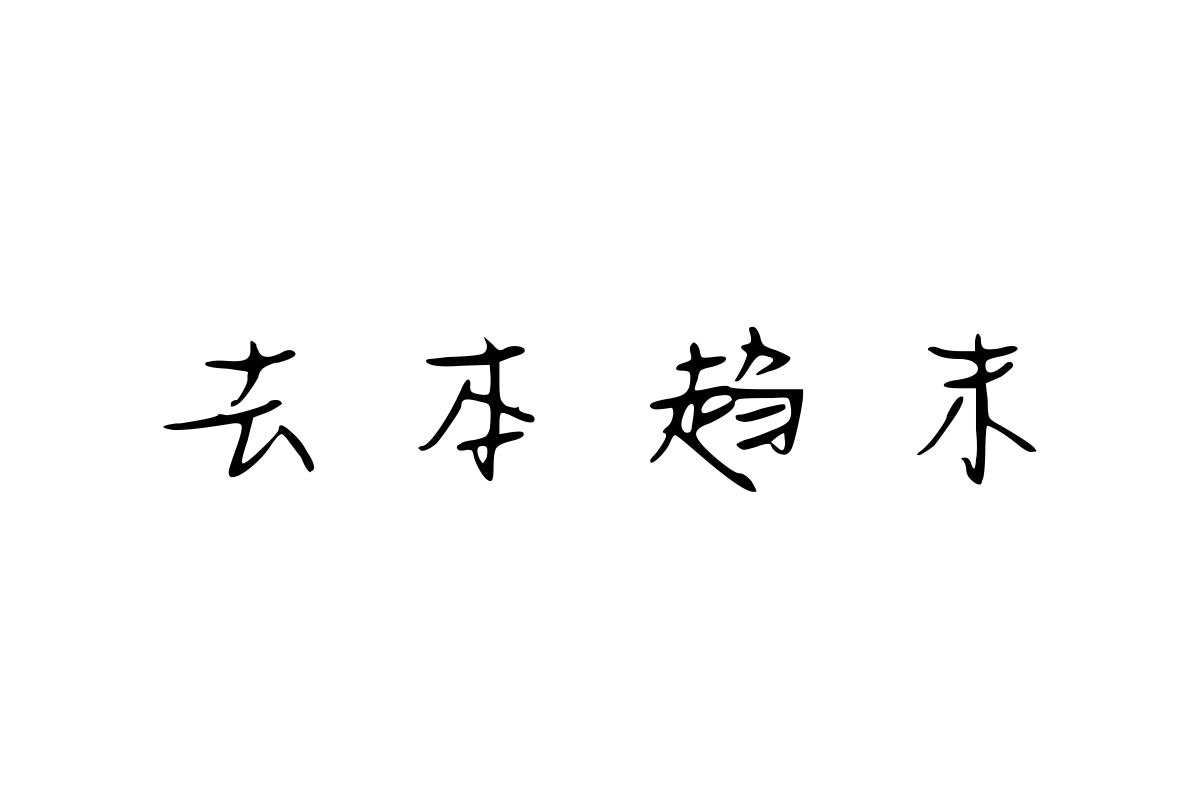
汉呈丹丹惠质如兰是一款具有独特风格的字体,其特点如下:
1. 字形优美:汉呈丹丹惠质如兰的字形优雅流畅,线条柔美,给人一种宁静、和谐的感觉。
2. 风格独特:这款字体具有独特的风格,不同于常见的宋体、楷书等字体,给人以新颖、别致的感觉。
3. 适用范围广泛:这款字体适用于各种场合,如标题、正文、广告、设计等,具有较高的实用性和通用性。
4. 易于识别:汉呈丹丹惠质如兰的字形简洁明了,易于识别,方便人们快速阅读和理解。
总之,汉呈丹丹惠质如兰是一款具有独特风格和实用性的字体,适用于各种场合,给人带来愉悦的视觉体验。